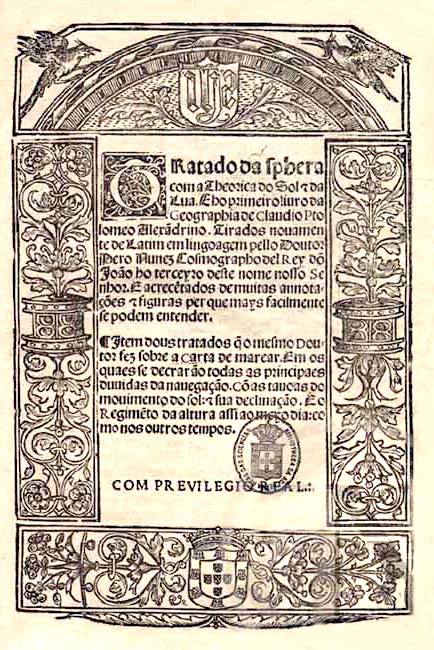
German Gaillard (séc. XVI)German Galharde ou Germão Galharte Tipógrafo francês que se estabeleceu em Lisboa a partir de 1519, adoptando o nome German Galharde ou Germão Galharte. Este tipógrafo imprimiu em Lisboa e em Coimbra.German Gaillard adquiriu aos herdeiros de Valentim Fernandes o material tipográfico com que imprimiu em 1519, uma das suas primeiras edições, o Missale secundum consuetudinem. Em 1530 e 1531 foi impressor do Mosteiro de Santa Cruz. Em 1535 foi encarregado por Dionisio de Moraes de pôr a funcionar a oficina tipográfica do Mosteiro de Santa Cruz de Coimbra. Em 1530 Gaillard foi distinguido por João III com os privilégios e liberdades dos «oficiais mecânicos» da Casa Real. «Dom Joham ... aquamtos esta carta virem faço saber que, querendo eu fazer graça e merce a germão galharte, emprymidor morador nesta cydade de lixboa, por esta presemte carta me praz o tomar e auer por meu e quero e mando que goze de todos os priuilégios e liberdades de que gozam os meus oficyaes mecanicos, e asy que lhe nom seyam tomadas d apousemtadorya pera nenhuas pesoas que seyam as casas em que elle vyuer e morar e em que teuer a tenda do seu oficyo, aimda que seyam alugadas sem embargo do regimento de apousemtadorya. (...) Dada em Lisboa a xiiij de feuereiro, Jorge Roiz a fez, anno ... de mill bc.xxx». Da oficina lisboeta de Gaillard/Galharde saiu, em 1534, a mais conhecida obra por ele impressa: a Cartinha para ensinar a ler de Diogo Ortiz de Vilhegas. Esta impressão é anterior à licença que o tipógrafo obteve de João III para imprimir, durante dez anos, a Cartinha do bispo de Viseu, e o Reportório dos Tempos. Em 1536, Galharde imprimiu a importante obra Grammatica da lingoagem portuguesa de Fernão de Oliveira (1507-1581). Desta obra existe um exemplar de grande raridade, comprado pela Biblioteca Nacional em 1867. Aponte-se que também os livros da oficina de Galharde foram predominantemente impressos em caracteres góticos.
Tratado da sphera com a Theorica do Sol i da Lua, tradução do matemático Pedro Nunes do primeiro livro da Geographia de Claudio Ptolomeo. Lixboa : per Germão Galharde empremidor, 1 Dezembro 1537 Apesar de este livro ter sido composto «tradicionalmente» com tipos da Gótica rotunda, algumas letras faltaram na caixa de composição e foram substituídas por tipos romanos. A última linha também foi composta com romanas... Actividades em CoimbraEm Coimbra, Germão Galharde instalou um prelo no Mosteiro de Santa Cruz, em 1530-31. Em 1567, a cidade de Coimbra tinha, para além desta tipografia, um impressor na freguesia de São Salvador e um outro na freguesia de São Pedro. Sob os auspícios de João III é instalada em 1530 uma imprensa. A instalação de uma oficina tipográfica no interior dos claustros teve como objectivo a ocupação do cónegos em trabalho útil, e também facultar a impressão de livros relacionados com a formação espiritual e ordenações internas que seriam depois distribuídos pelas restantes casas da congregação. Os frades trocam a pena de calígrafo pela composição de caracteres. Teria sido João III, protector do Mosteiro, que pagou a instalação da oficina e da totalidade dos instrumentos necessários. Para instruir os monges no ofício tipográfico, os cónegos de Santa Cruz vão socorrer-se de German Galharde. Este permaneceu dois anos em Santa Cruz, tempo suficiente para os frades adquirirem o domínio das artes tipográficas. Durante este período imprimiu seis obras. A primeira obra impressa sob a sua direcção foi uma pequena publicação com seis folhas não numeradas, em língua portuguesa, o Reportorio pera se acharem as materias no livro Spelho de Conciencia, saído dos prelos do Convento a 9 de Agosto de 1530. Com a impressão deste índice do livro Spelho da Conciencia, pertencente a uma edição castelhana impressa em 1525, German Galharde procurou demonstrar o alcance técnico da arte tipográfica. Em Abril do ano seguinte, imprimem o Breuiarium secundum monasteri Sancta Crucis Colimbriensis ordinis diui Augusti, livro auxiliar para as orações quotidianas adaptadas aos usos e costumes da vivência monástica do Convento de Santa Cruz. Esta publicação viria a ser a mais extensa das impressões crúzias, contando com cerca de 586 folhas, impressas a duas colunas e a a preto e vermelho. Depois de instruídos na impressão, os cónegos regrantes tomam em mão os instrumentos e passam a ser eles a compor e imprimir. Até 1563 imprimiram 21 obras. É mais que provável que o material tipográfico e gravuras utilizadas tenham proveniência estrangeira. Os tipos e as inúmeras iniciais gravadas com diversos motivos, a composição das páginas de rosto com tarjas e gravuras talhadas em madeira, as cercaduras onde se inscrevam os títulos e composições de entalhe inteiro como é o caso de algumas portadas e gravuras, pelo apuro da sua técnica indicam que teriam sido importadas. DigitalizaçõesChiado, António Ribeiro, 1520?-1591 Auto das regateyras per Antonio Ribeyro. Pratica de treze figuras, Velha, Briatiz, Negra, Comadre, Pero Vaz, Noyuo, May, Ioã Duarte, Afonso Tome, Frenã Dãdrade, Gomez Godinho, Brimanesa. - [Lisboa] : German Galharde, [até 1536?]. - [10] f. : il. ; 4º (20 cm) http://purl.pt/6932 Oliveira, Fernando 1507-ca 1581 Grammatica da lingoagem portuguesa / [Fernão Doliueira]. - Em Lixboa : e[m] casa d`Germão Galharde, 27 Ianeyro 1536. - [38] f. ; 4º (20 cm) http://purl.pt/120 PublicaçõesOliveira, Fernão, 1507-ca. 1581 Gramática da linguagem portuguesa / Fernão de Oliveira. - Lisboa : Biblioteca Nacional, 1981. - [82] p. ; 21 cm. - fac-simile da ed. de Lisboa, de Germão Galharde, em 1536 31000 HIS OLI*GRA - 4878 |